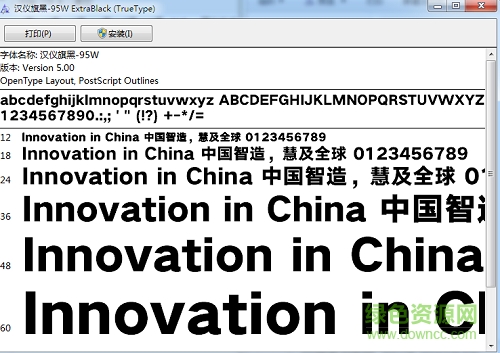
hyqihei iew
hyqihei iew字體又稱(chēng)漢儀旗黑95w字體,是一款非常醒目的中文字體,字形筆畫(huà)粗獷有力,筆畫(huà)細(xì)節(jié)上的修飾既增強(qiáng)了字體的設(shè)計(jì)感,有喜歡的朋友歡迎來(lái)綠色資源網(wǎng)下載使用!
hyqihei iew字體簡(jiǎn)介
hyqihei iew字體是一款極具個(gè)性的黑體字體,字體非常端莊大方,可以廣泛應(yīng)用于廣告設(shè)計(jì)、宣傳海報(bào)、ppt、影視制作以及任何使用文字的領(lǐng)域!